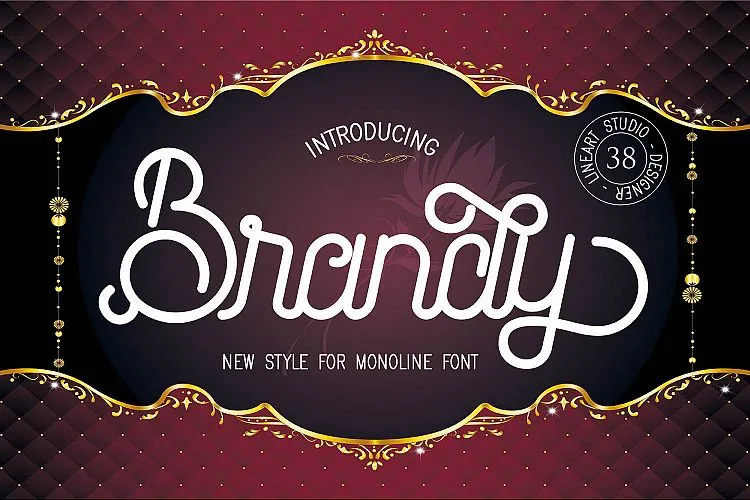
Brandy Monoline Font Duo – Download Grátis
Descubra a Brandy Monoline Font Duo, uma paixanteira escolha para qualquer projeto que valoriza os estilos antigos do tipo de letra. Inspirada na arte tipográfica tradicional, esta família de fontes vintage é composta por duas versões: uma script elegante e outra em estilo sans-serif, complementando-se perfeitamente umas às outras. Esta dupla monoline, criada pelo designer 24Design, foi inspirada no estilo do tipo moderno e conta com duas opções para escolha – Brandy Script e Sheriff. O Brandy Script apresenta duas variações: uma versão limpa e outra mais natural, garantindo diversidade de expressões. Este conjunto de fontes é um verdadeiro hit para quem busca uma fusão perfeita entre o estilo clássico e o moderno, oferecendo um toque vintage ao seu design sem perder a relevância contemporânea.